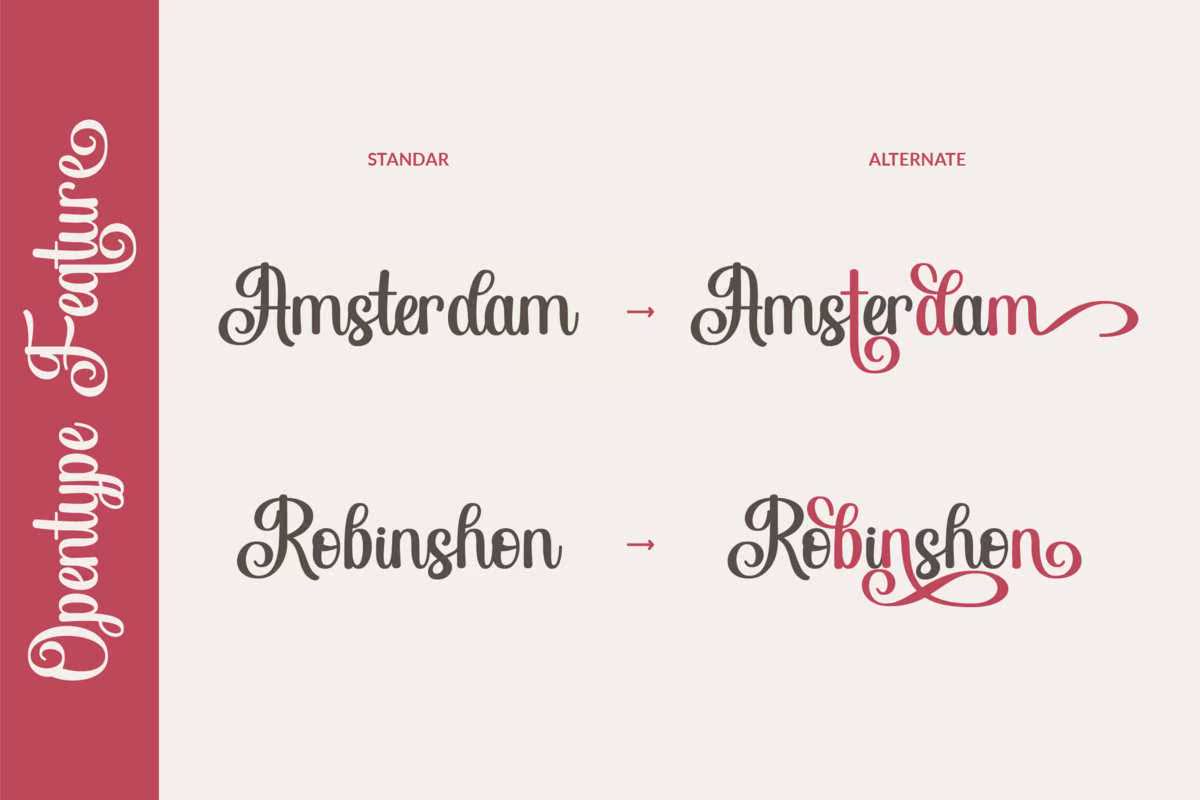
Handofking是一款美观、甜美的手写字体。它清新、干净、美观。功能强大,是一款集设计于一体的字体,将其提升到了最高水平。令人惊讶的是,您的名片、报价单、婚礼宣传单、贺卡、名片、,需要手动触摸的徽标和任何其他设计。此字体是经过编码的,表示您可以访问符号和开关!Handofking是一款美观、甜美的手写字体。它清新、干净、美观。功能强大,是一款集设计于一体的字体,将其提升到了最高水平。令人惊讶的是,您的名片、报价单、婚礼宣传单、贺卡、名片、,需要手动触摸的徽标和任何其他设计。此字体是经过编码的,表示您可以访问符号和开关!